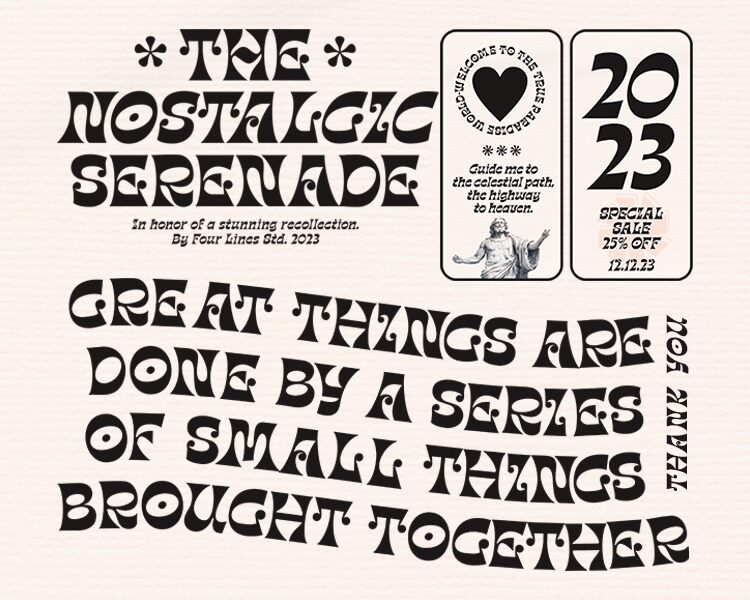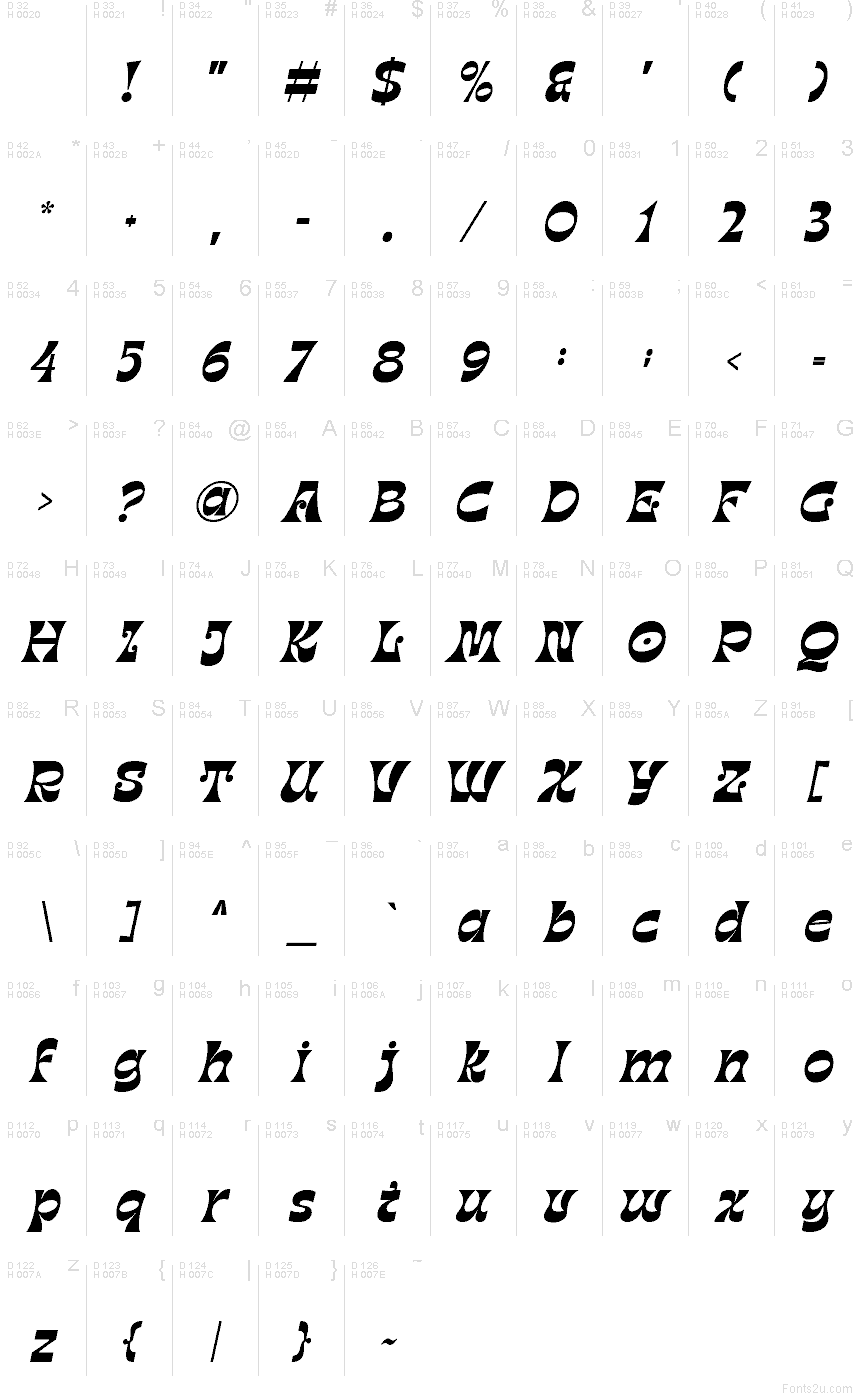
Nostalgic Serenade Italic
La police Nostalgic Serenade Italic du studio Four Line Studio est une fonte d’affichage groovy gratuite, dotée d’une inclinaison italique fluide, de courbes arrondies et de lignes douces qui donnent aux lettres un rythme décontracté, évoquant les affiches musicales d’autrefois. Ses formes, façonnées par de longs arcs et des espaces intérieurs ouverts, permettent à chaque caractère de s'enchaîner avec naturel, conservant une ligne vivante sans jamais paraître rigide.
Nostalgic Serenade Italic est idéale pour les affiches rétro, les pochettes d’albums, l’identité visuelle de cafés, les flyers d’événements et les logos courts. Ses formes incurvées offrent une signature décorative affirmée sans sacrifier la lisibilité. Cette police gratuite est parfaite pour les titres, les visuels de réseaux sociaux et les packagings qui nécessitent une esthétique chaleureuse et nostalgique pour capter immédiatement l’attention.